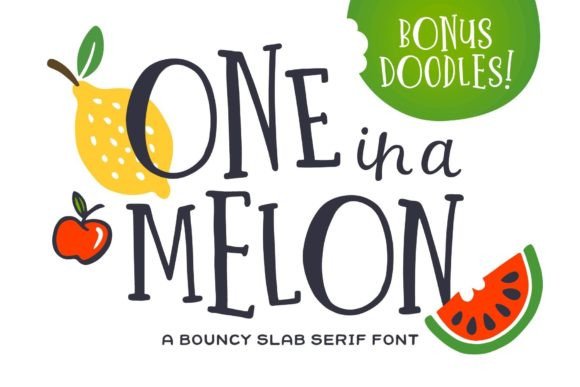
One in a Melon
One in a Melon – A Fonte que Transforma Seu Verão em Arte
Se você está à procura de uma tipografia que combine leveza, diversão e um toque bouncy para projetos de verão, One in a Melon chega na medida certa. Esta fonte all‑caps slab serif destaca‑se tanto em títulos grandiosos quanto em textos menores, garantindo legibilidade sem perder o charme tropical.
- Estilo all‑caps slab serif: linhas robustas que dão presença, mas com cantos suavizados que mantêm a sensação descontraída.
- Versatilidade de tamanho: funciona perfeitamente em cartazes de grande escala e também em legendas ou botões pequenos.
Por que One in a Melon é a Escolha Ideal para Projetos de Verão?
O verão pede cores vibrantes e tipografias que transmitam energia. One in a Melon entrega exatamente isso:
- Impacto visual imediato: o formato all‑caps cria títulos que chamam a atenção à primeira vista.
- Atmosfera lúdica: os doodles de frutas adicionam um toque de “verão tropical” sem esforço.
Como Usar One in a Melon no Seu Próximo Projeto
2. Escolha o tamanho adequado – experimente 120 pt para banners, 48 pt para posts de mídia social e 24 pt para chamadas de ação menores.
3. Adicione os doodles de frutas como elementos de apoio; eles funcionam bem como marcadores, fundos ou bordas decorativas.
4. Combine cores de verão – laranjas, amarelos e verdes frescos realçam ainda mais o estilo da fonte.
5. Teste a legibilidade em diferentes dispositivos para garantir que o efeito “bouncy” não comprometa a leitura.
Conclusão – Vale a Pena?
Com seu design alegre, alta legibilidade e um pacote completo de recursos gráficos, One in a Melon é a escolha número‑um para designers que querem dar vida a campanhas de verão, eventos ao ar livre, menus de sorvete ou qualquer material que precise de um toque refrescante. Experimente agora e veja como a sua comunicação visual ganha um sabor irresistível!